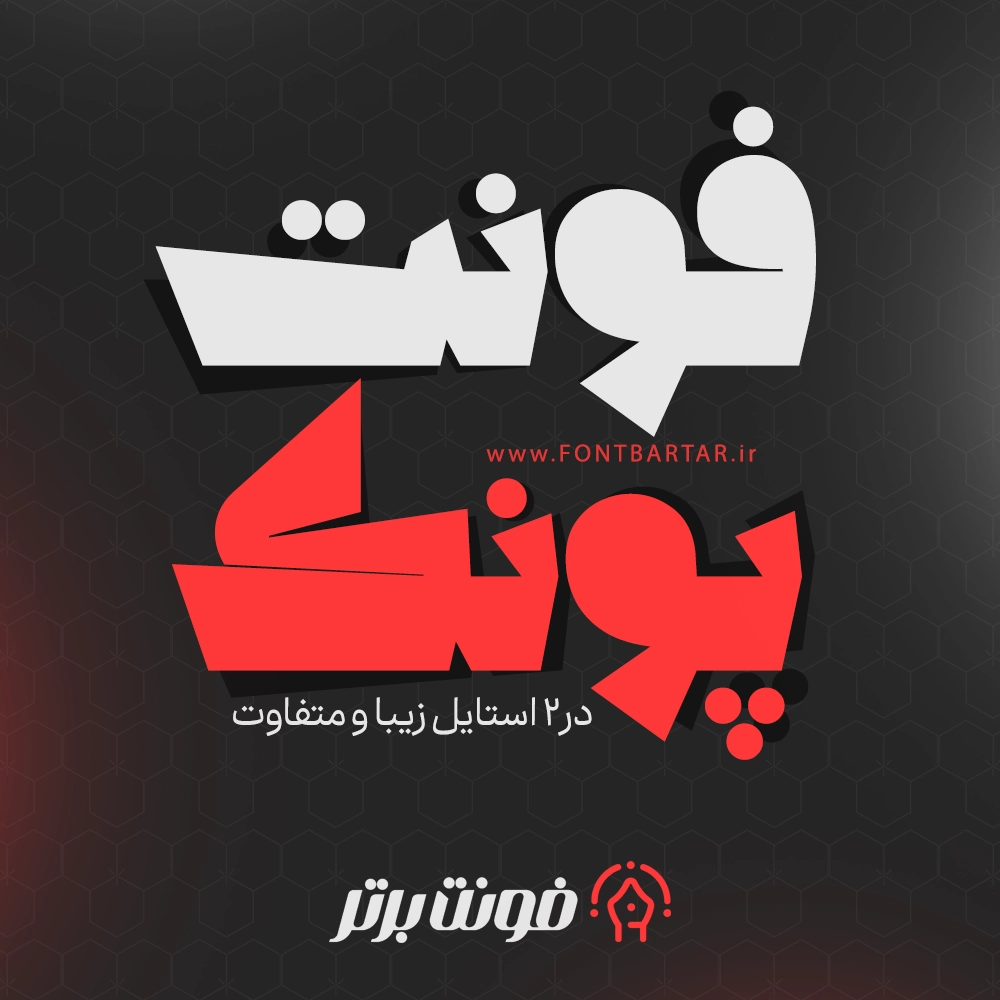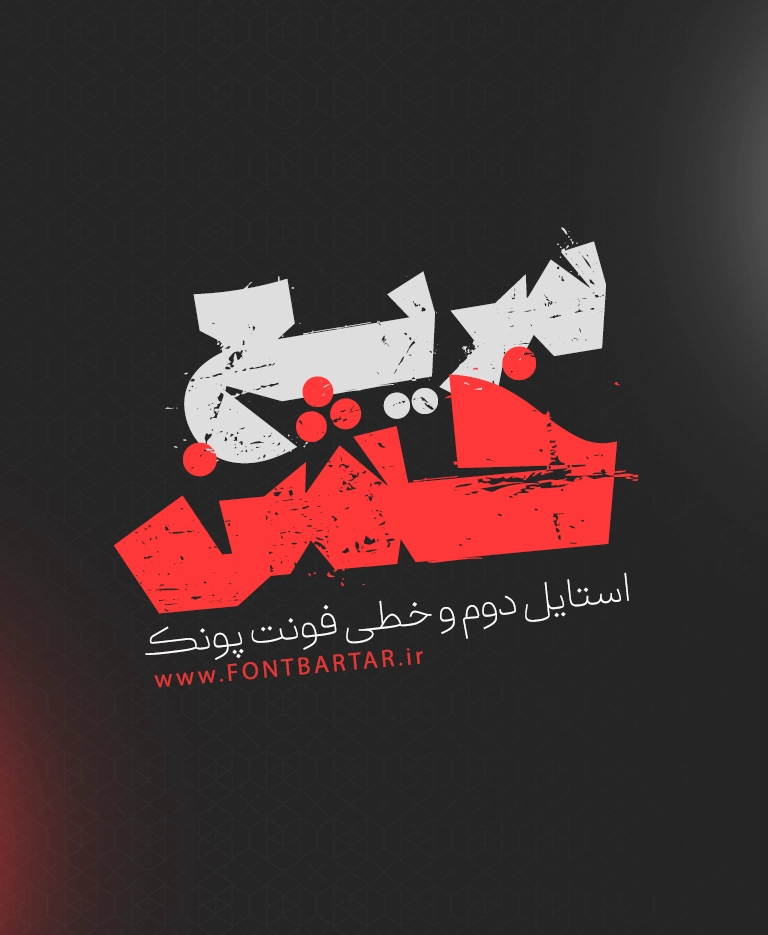
دانلود فونت پونک – فونت فونت زیبا در دو استایل جذاب
فونت پونک یکی از متفاوتترین و چشمگیرترین فونتهای نمایشی فارسی است که بهطور ویژه برای طراحی پوسترهای تبلیغاتی، کاورهای حرفهای، لوگوتایپهای خلاق و طرحهای گرافیکی قدرتمند ساخته شده است. فونت زیبا پونک با یک ساختار هندسی خاص، زاویههای تیز و ترکیب خطوط حجمی، توانسته به انتخاب اصلی طراحانی تبدیل شود که قصد دارند طرحی متفاوت، خاص و کاملاً متمایز ارائه دهند.
این فونت زیبا فارسی در ۲ استایل زیبا و منحصربهفرد طراحی شده و همین تنوع باعث شده تا در پروژههای مختلف، از طراحی رسمی گرفته تا استایل پرانرژی و هیجانی، کاربرد داشته باشد.
چرا فونت پونک برای طراحان ضروری است؟
وقتی صحبت از یک فونت نمایشی حرفهای میشود، چند ویژگی اساسی اهمیت پیدا میکند:
خرید فونت زیبا خوانایی، جذابیت بصری، ساختار مستحکم و هماهنگی با فضای برند. فونت پونک دقیقاً بر همین اساس طراحی شده است.
مزایای مهم فونت پونک :
- ترکیب خطوط زاویهدار و هندسی مناسب طراحیهای هیجانی
- فونت خاص پونک استایل جسورانه و قدرتمند مناسب پوستر و کاور
- فونت زیبا جدید ارائه شده در دو نسخه با حس بصری متفاوت
- مناسب تایپوگرافیهای حرفهای و ترکیب متنهای کوتاه
- فونت زیبا طراحی مناسب هویت بصری برندهای مدرن و جوان
ویژگیهای اصلی فونت پونک :
طراحی مدرن و چشمگیر فونت زیبا پونک
فرمهای نامتقارن و برشهای تیز در این فونت باعث شده تا در اولین نگاه، توجه مخاطب به متن جلب شود. این ویژگی باعث شده فونت پونک برای طراحی پوسترهای مهم و فوری انتخابی قدرتمند باشد.
ارائه فونت خاص پونک در دو استایل حرفهای
دو نسخه موجود این فونت به طراح امکان انتخاب سبک مناسب را میدهد.
فونت فارسی سازگار با تمامی پروژههای تبلیغاتی
از کاور موزیک گرفته تا طراحی بنر فروشگاهی و لوگوتایپ، فونت پونک در هر پروژهای بدرخشید.
کاربردهای خرید فونت فارسی پونک
- طراحی پوسترهای تبلیغاتی
- کاور موزیک و آلبوم
- طراحی لوگوتایپهای خلاق
- بنرهای فروشگاهی و مناسبتی
- طراحی استوری و پست اینستاگرام
- تصاویر شاخص وبسایتها
- تایپوگرافی حجمی و گرافیکی
- طرحهای گیمینگ و ورزشی
⭐ FAQ سؤالات متداول درباره فونت پونک
1. فونت پونک در چه پروژههایی بهترین عملکرد را دارد؟
در پوستر، لوگوتایپ، کاور موزیک، بنر تبلیغاتی و هر طرحی که نیاز به یک سبک نمایشی قدرتمند دارد.
2. آیا این فونت برای متنهای طولانی مناسب است؟
خیر. این فونت یک فونت نمایشی است و بهترین عملکرد آن در عنوانها و تیترهای مهم است.